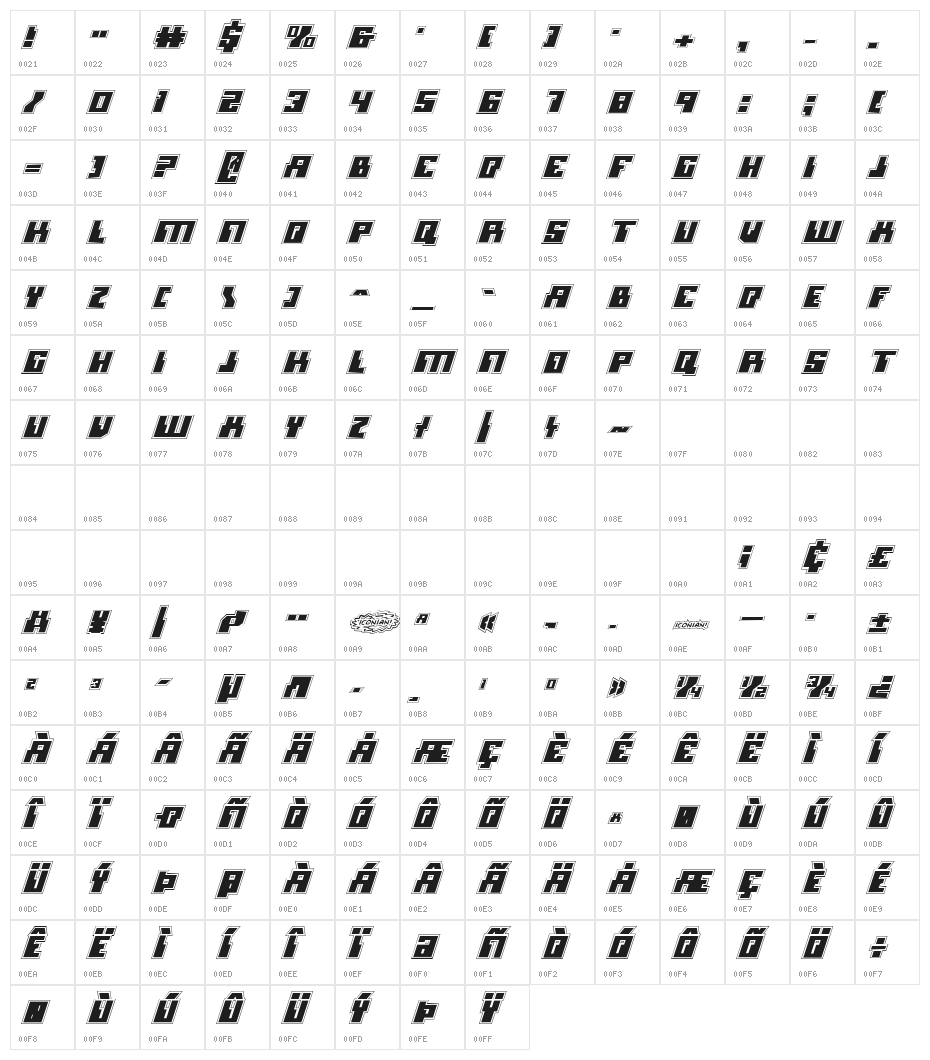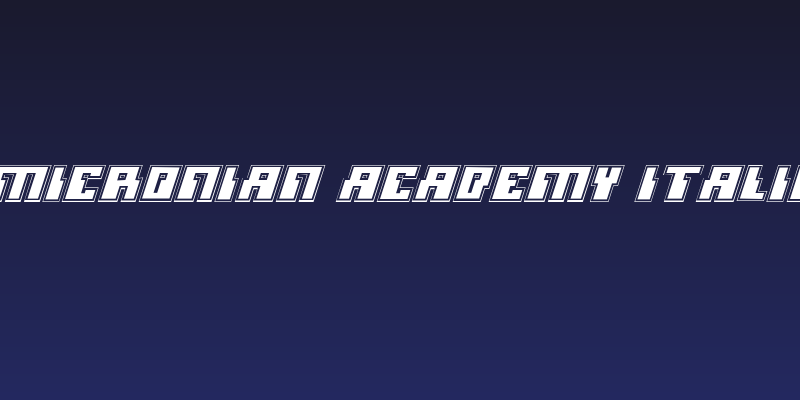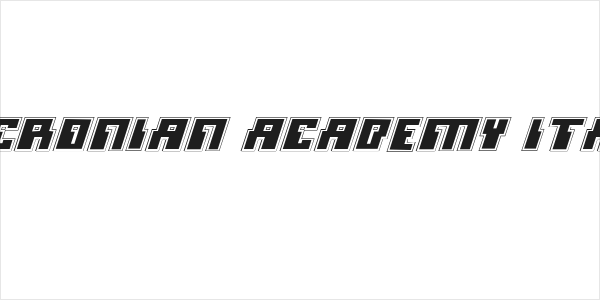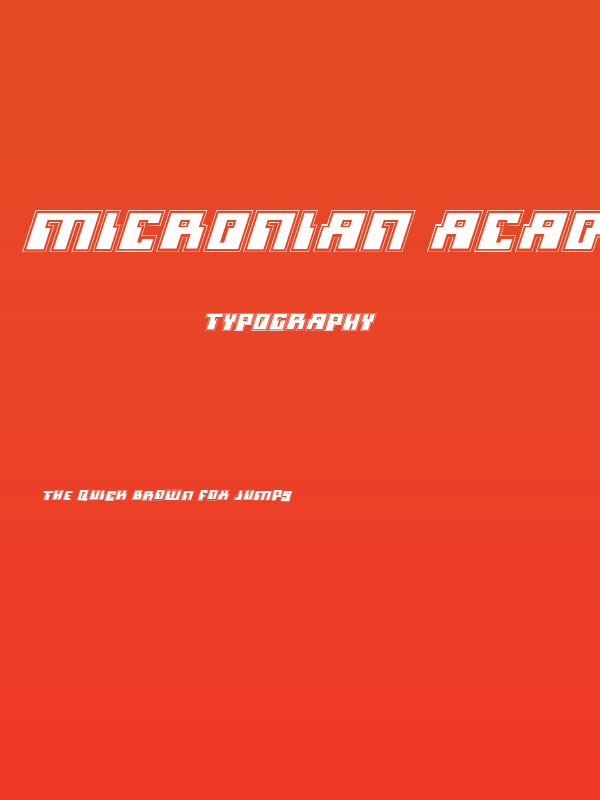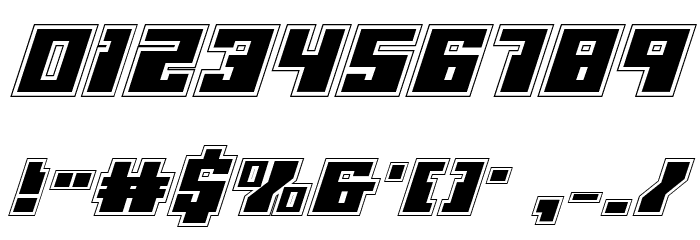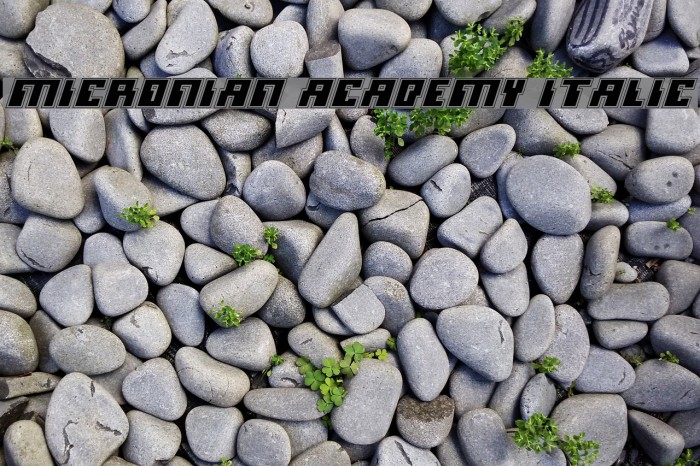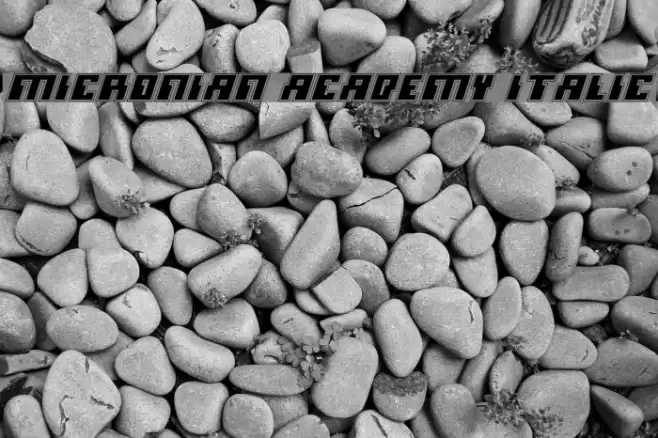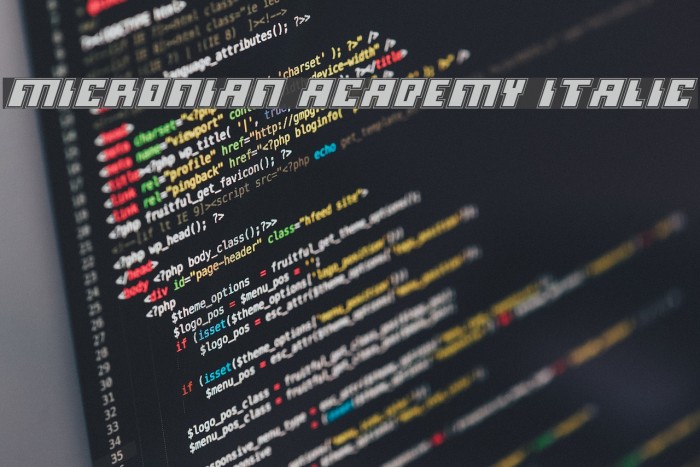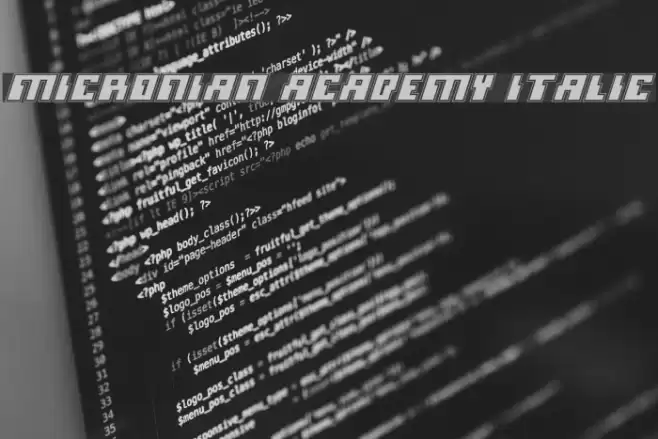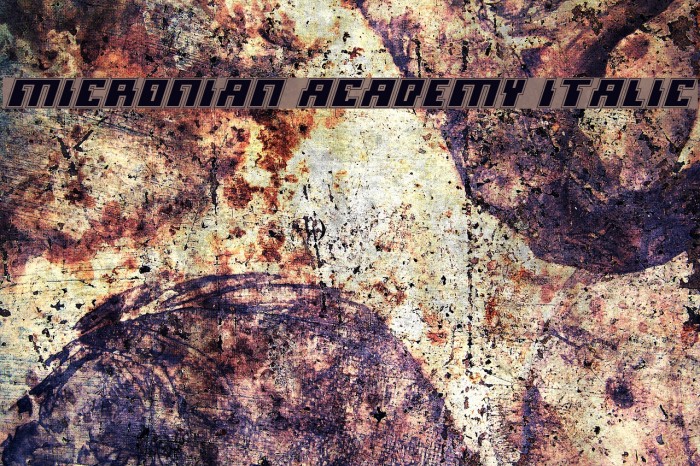
Micronian Academy Italic Font
✎ Futuristic
| Vorgeschlagene Projekte | Ideal for sci-fi themed designs, video game titles, tech branding, and modern posters. |